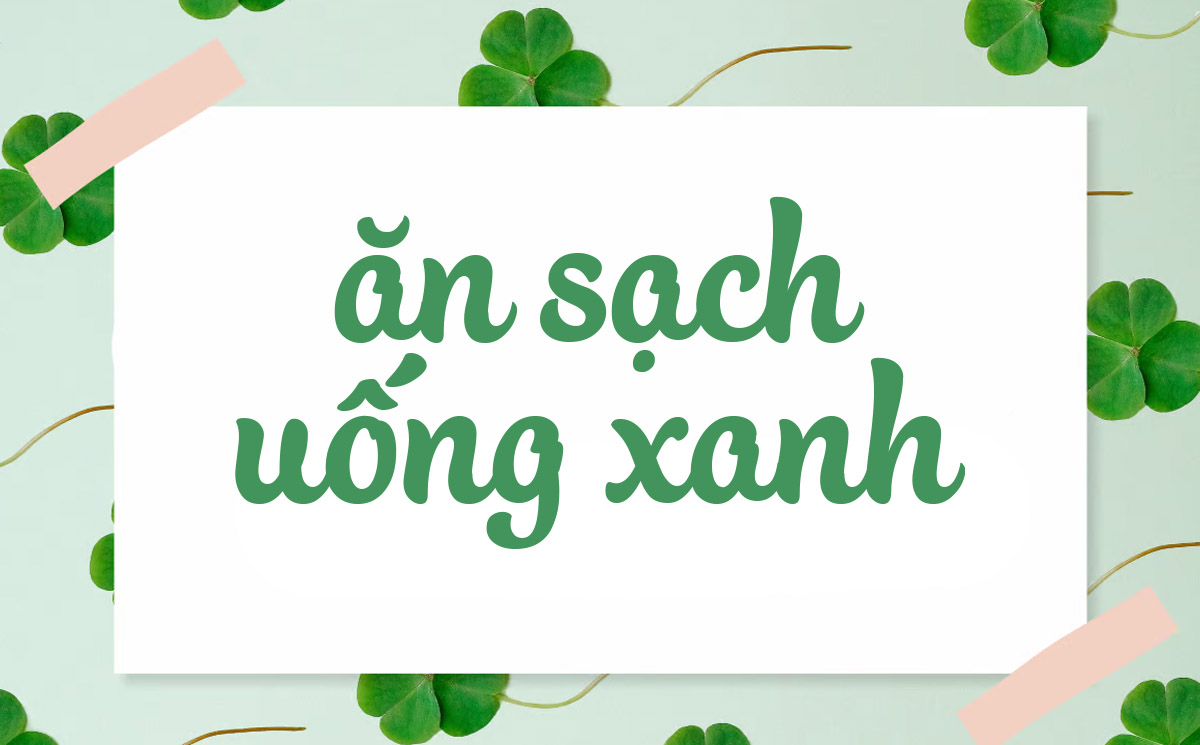
Nếu bạn đang tìm kiếm một phông chữ mang lại cảm giác vui tươi, nhẹ nhàng và đáng yêu cho các dự án thiết kế của mình, thì Font chữ cute Việt hóa SVN Bali Script chắc chắn là một “vũ khí” không thể bỏ qua. Sự kết hợp giữa nét chữ viết tay phóng khoáng và sắc thái ngọt ngào giúp bộ font này dễ dàng chinh phục mọi ánh nhìn.
Giới Thiệu Về Font SVN Bali Script
SVN Bali Script là một phông chữ mô phỏng nét viết tay (handwritten script) với những đường cong mềm mại và uyển chuyển. Khác với những phông chữ script mang tính trang trọng, cổ điển, Bali Script toát lên sự trẻ trung, hiện đại và vô cùng “cute”. Phiên bản Việt hóa (SVN) đã được xử lý kỹ lưỡng, giúp các nhà thiết kế hoàn toàn yên tâm gõ tiếng Việt có dấu mà không lo đứt gãy hay lỗi hiển thị ký tự.
Đặc Điểm Nổi Bật Của SVN Bali Script
Bộ font này sở hữu nhiều ưu điểm khiến nó trở thành lựa chọn yêu thích trong cộng đồng thiết kế:
• Bộ dấu tiếng Việt hoàn hảo: Các dấu câu được tinh chỉnh và đặt ở vị trí cân đối, hài hòa tuyệt đối với từng con chữ, giữ nguyên nét duyên dáng của bản gốc.
• Phong cách tự nhiên: Các ký tự có độ cao và độ nghiêng không đồng đều một cách có chủ đích, tạo cảm giác chân thực giống như nét chữ viết tay hàng ngày nhưng vẫn đảm bảo tính thẩm mỹ cao.
• Dễ đọc (Legibility): Dù là một phông chữ kiểu script với các nét nối, SVN Bali Script vẫn có khoảng cách chữ (kerning) hợp lý, giúp văn bản dễ đọc ngay cả ở kích thước nhỏ.
Ứng Dụng Linh Hoạt Trong Thực Tế
Với sắc thái đáng yêu và trẻ trung, SVN Bali Script là lựa chọn tuyệt vời cho rất nhiều dự án sáng tạo:
• Thiết kế bao bì: Đặc biệt phù hợp cho các sản phẩm dành cho trẻ em, mỹ phẩm tuổi teen, bánh kẹo hoặc đồ handmade.
• Trích dẫn (Quotes) & Typo Mạng xã hội: Tạo ra những bức ảnh trích dẫn truyền cảm hứng cực kỳ thu hút trên Facebook, Instagram hay Pinterest.
• Nhận diện thương hiệu: Phù hợp làm logo cho các tiệm bánh ngọt, shop thời trang, tiệm hoa hoặc các dịch vụ chụp ảnh.
• Ấn phẩm sự kiện: Sử dụng trên thiệp cưới, thiệp mời sinh nhật, sổ lưu bút để mang lại cảm giác gần gũi, thân thương.